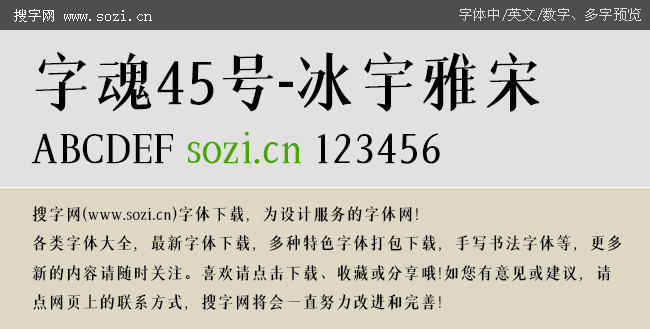
字魂45號-冰宇雅宋
搜字網(wǎng)提供一款字魂45號-冰宇雅宋中文字體下載,該字體是一款宋體字體,該字體包含6989個中文、字母、 符號和數(shù)字,具有現(xiàn)代、時尚、國際化、創(chuàng)意 的風(fēng)格,可以滿足您設(shè)計上的各種需求,該字體主要用于印刷品、印章、企業(yè)店鋪、廣告、新媒體、電商 等場景。